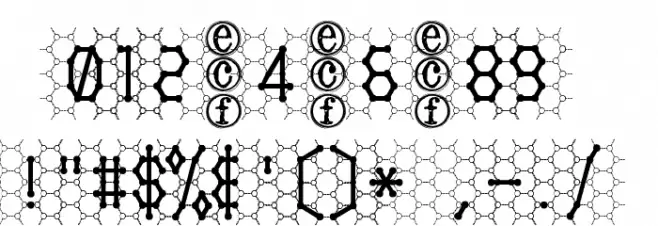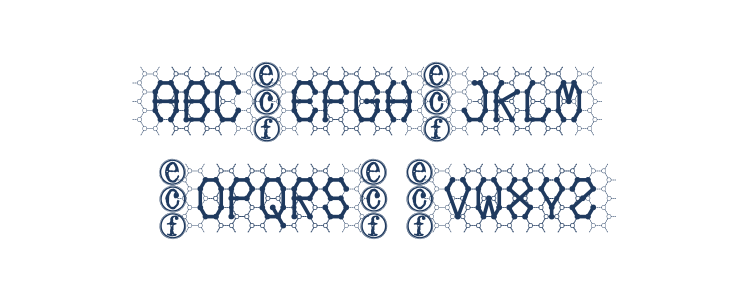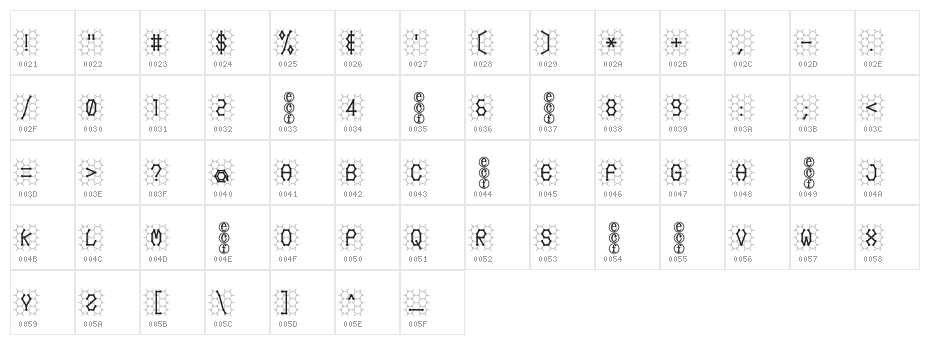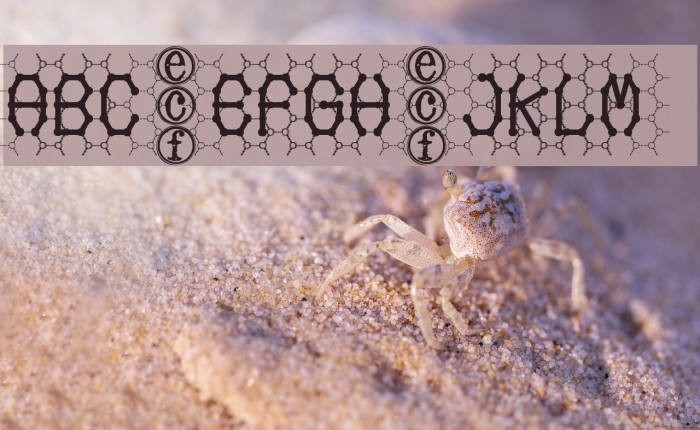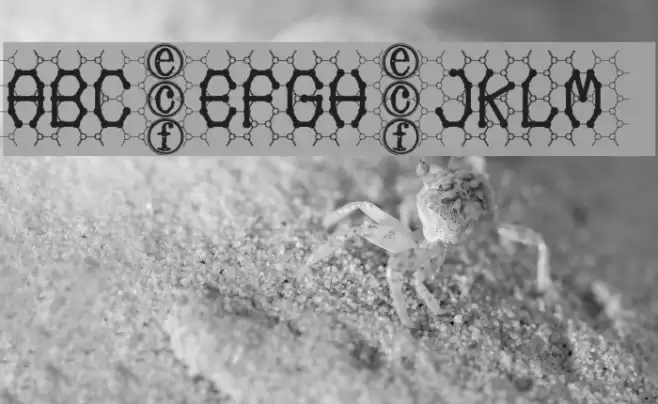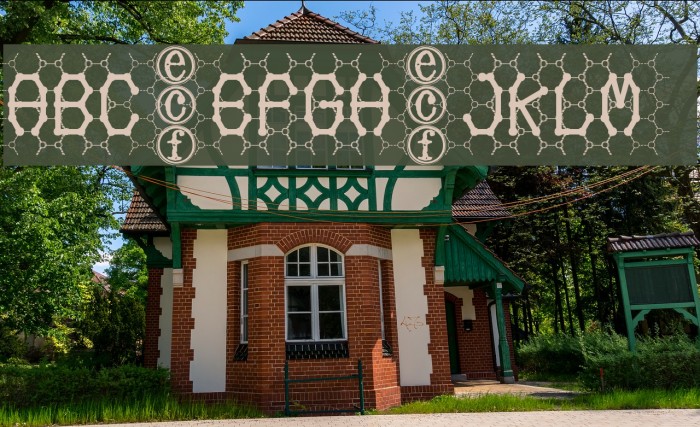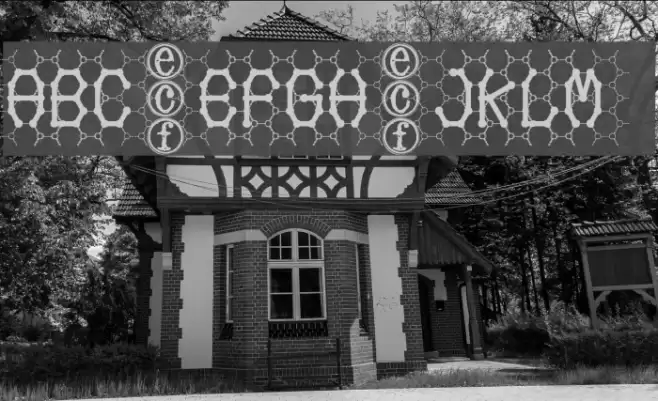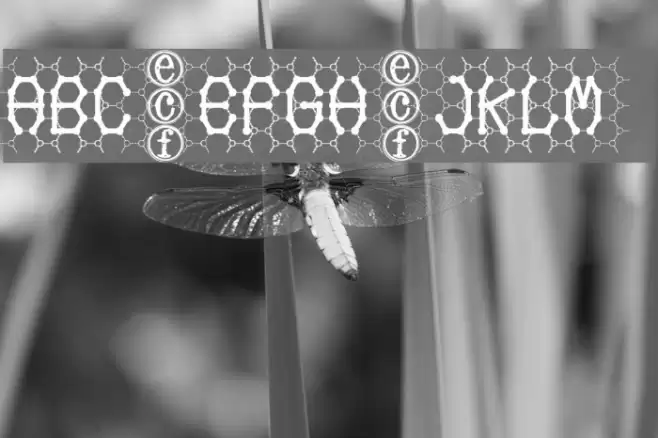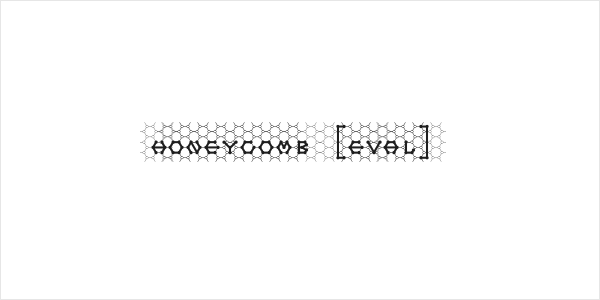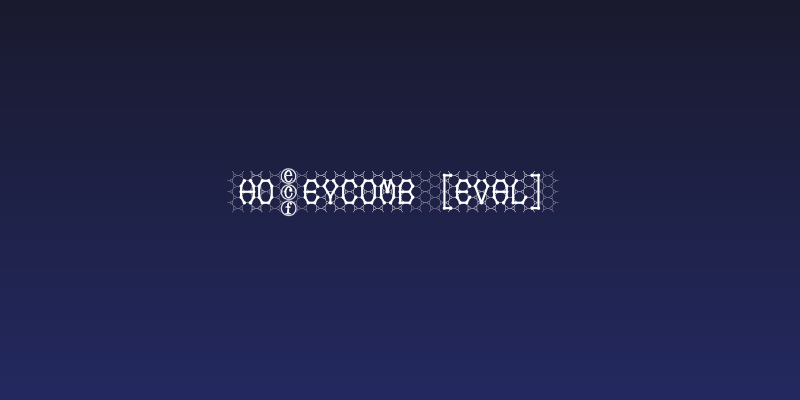
honeycomb [eval] Font
| Anwendungsfall | Logos, Posters, Headlines |
| Vorgeschlagene Projekte | Ideal for science-themed projects, tech branding, or any design requiring a modern and unique aesthetic. |